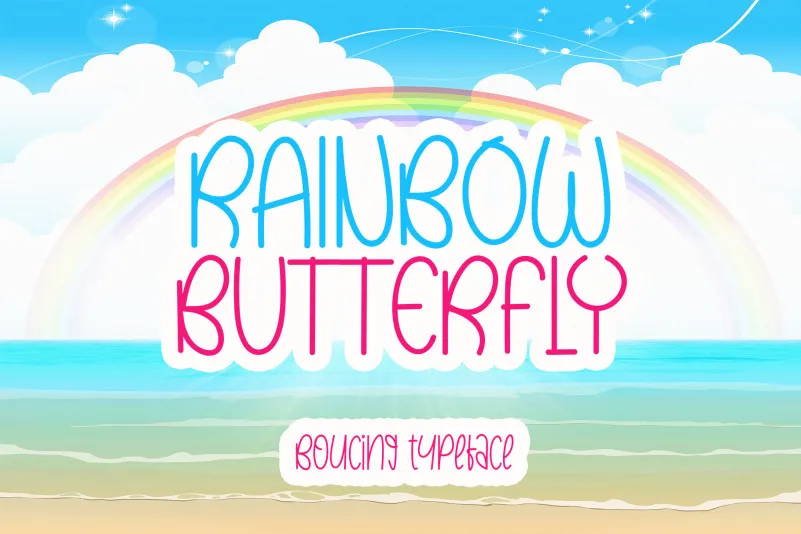
Rainbow Butterfly Font – Download Grátis
Esta é uma fonte exibição com um ar amigável e alegre. Embora genuína e divertida, ela se destaca especialmente para projetos temáticos infantis, perfeita quando combinada com cores vibrantes! Se você está procurando por uma fonte que não apenas complementa sua ideia visual, mas também traz vida e diversão, essa é a escolha certa. Composta de forma criativa, a Rainbow Butterfly Font de kateengciu pode fazer o seu projeto brilhar ainda mais, tornando-o um elemento especial em qualquer design.